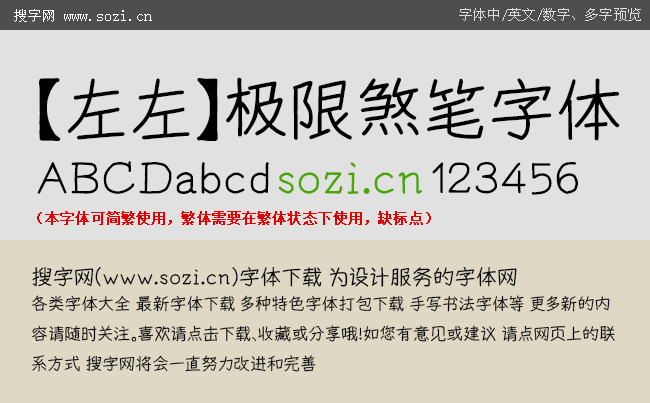
極限煞筆字體
搜字網(wǎng)給大家提供一款很卡通的手寫(xiě)風(fēng)格手機(jī)中文字體下載。修改者將它命名為極限煞筆字體,這款手機(jī)字體是是仿照兒童手寫(xiě)風(fēng)格的卡通手寫(xiě)字體。即有卡通字體的趣味性,又有手寫(xiě)字體的藝術(shù)性,特別適合喜歡手機(jī)字體個(gè)性一些的朋友在手機(jī)上安裝使用。